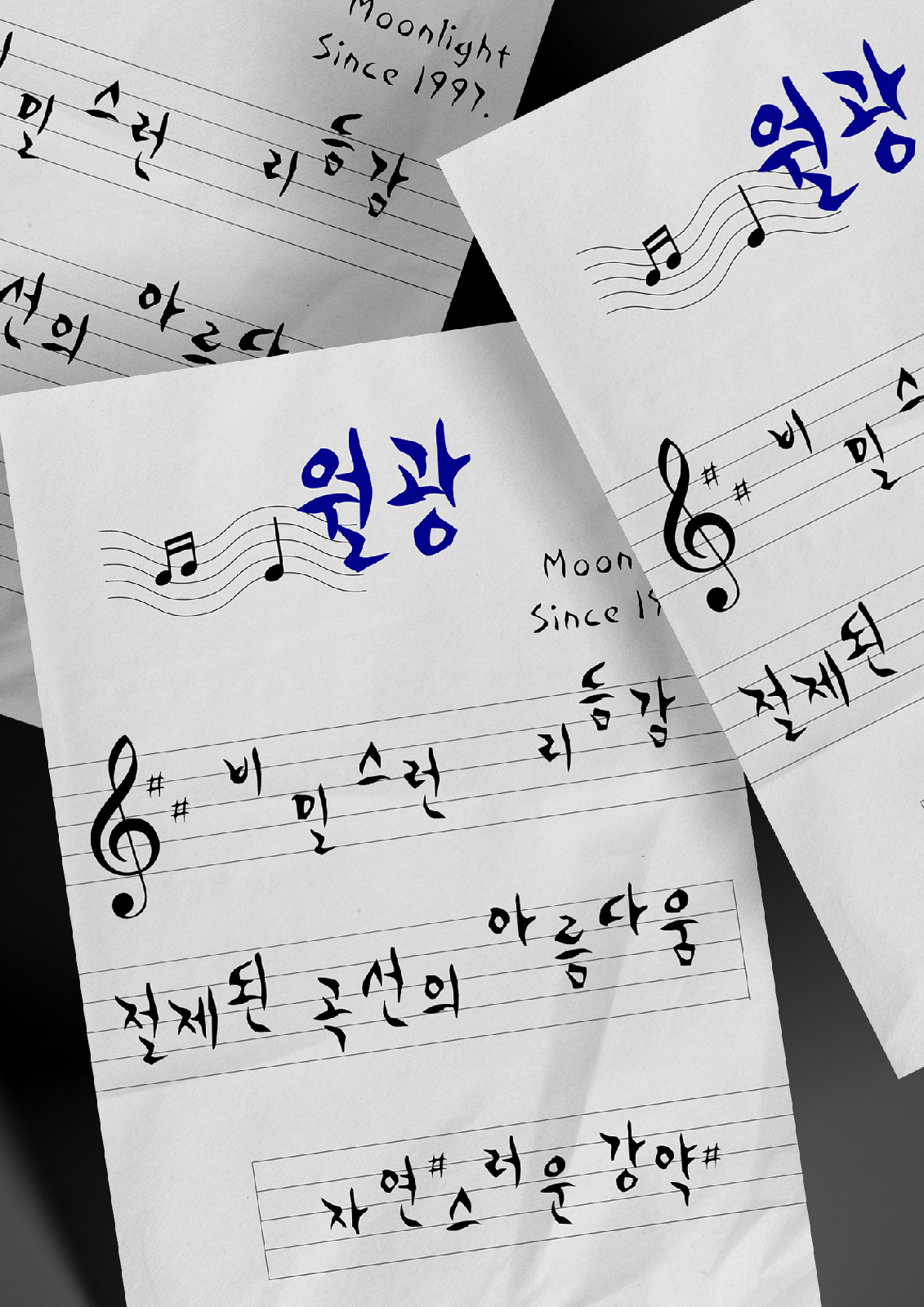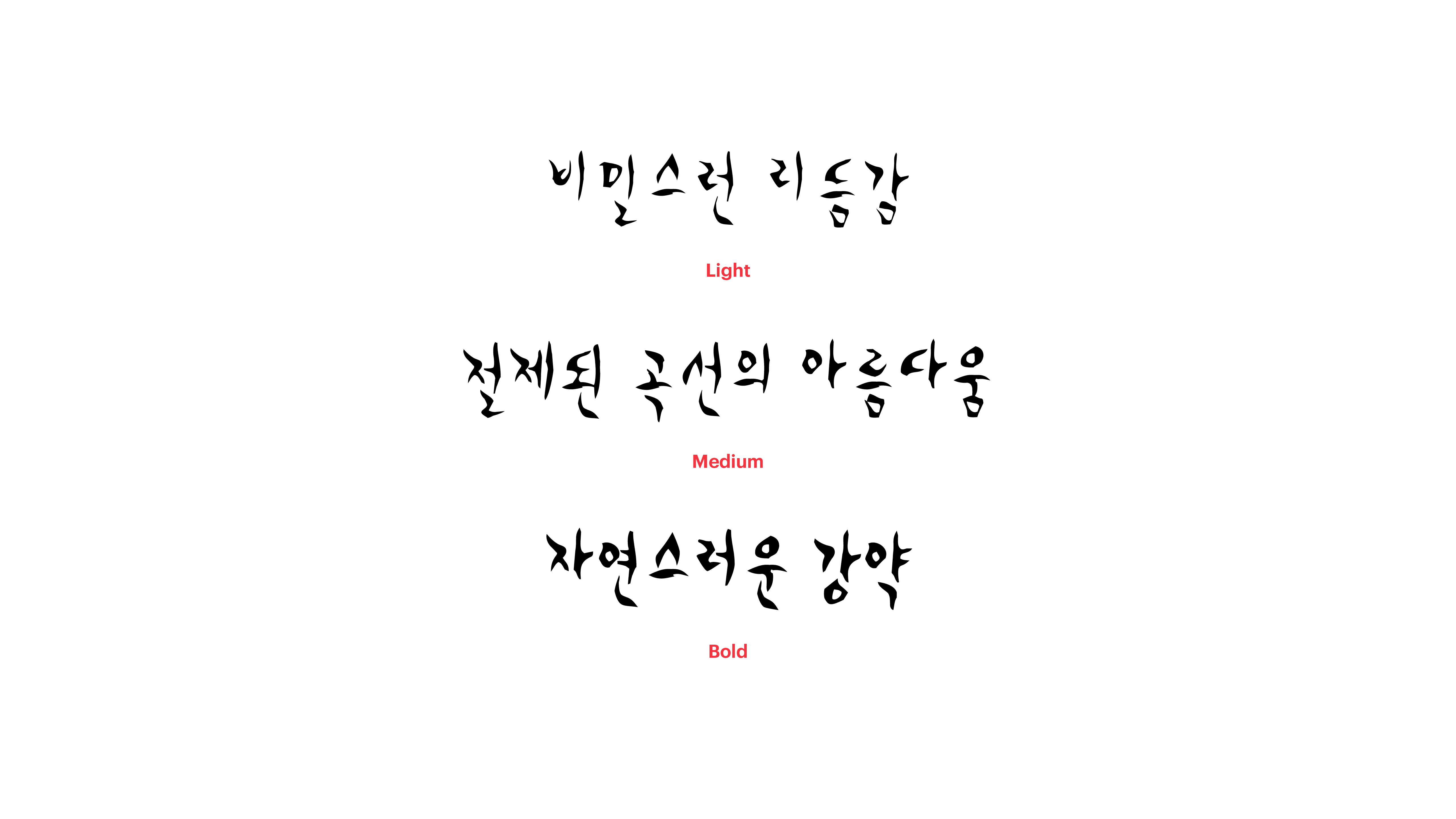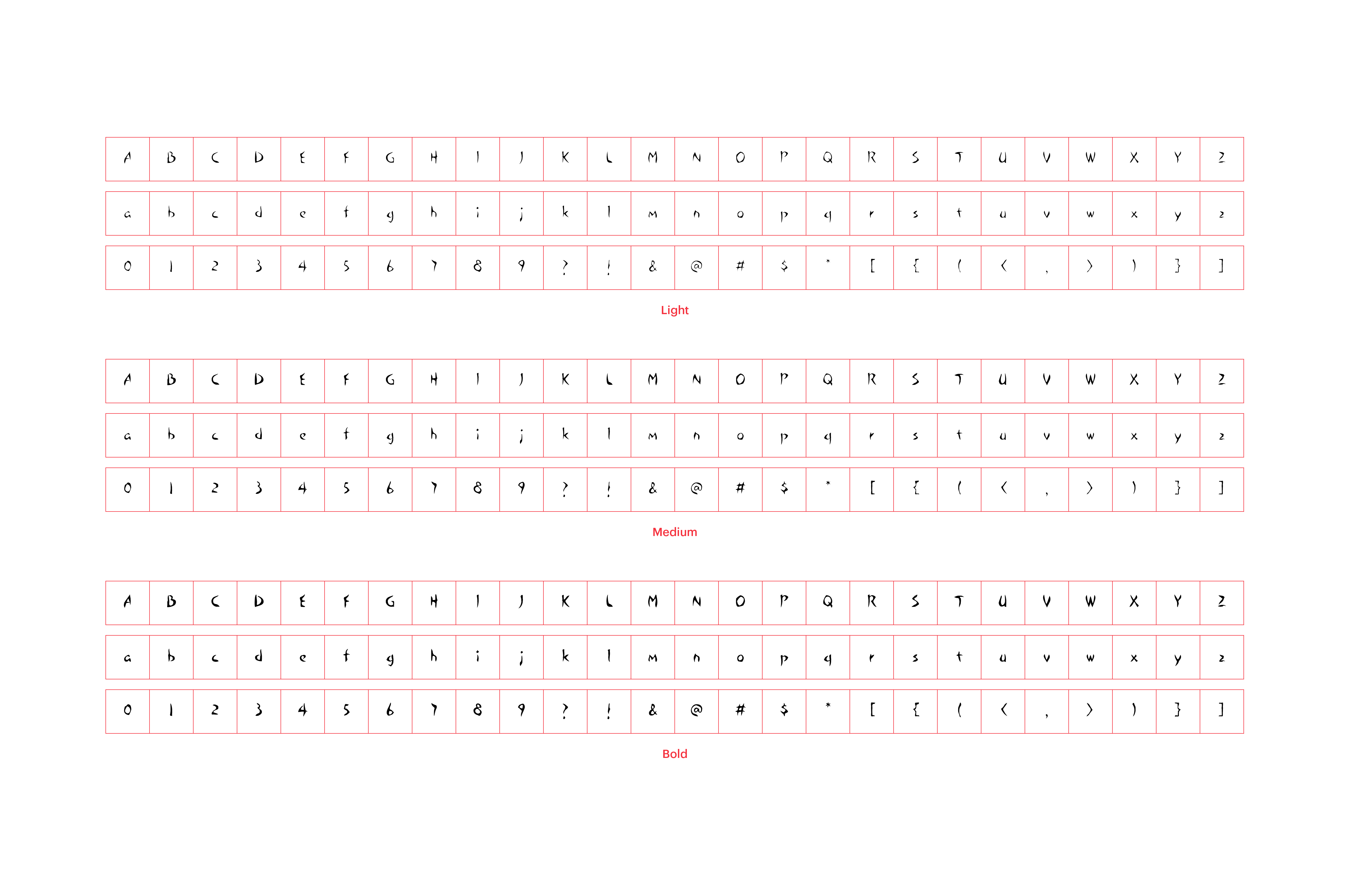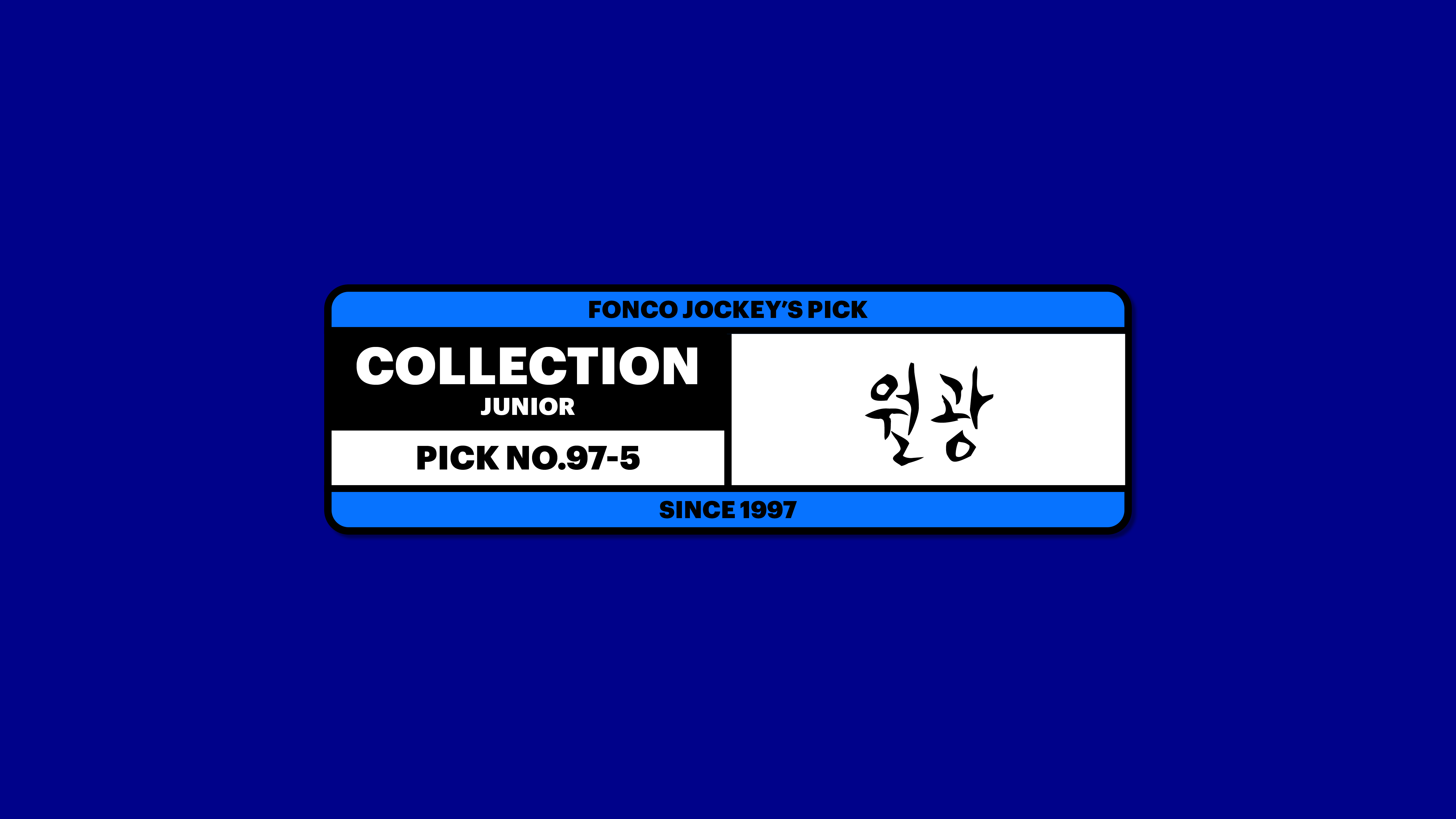
월광
Yoon 월광
달빛 아래에서는 폰트도 신비하게만 보일 겁니다. 월광체는 부드러운 달빛 그리고 삭망의 흐름에 담긴 비밀스런 리듬감을 절제된 곡선의 아름다움으로 표현하지요. 매일매일 조금씩 차오르거나 빠져나가는 달의 섭리와 같이, 자연스러운 강약을 지닌 폰트. 월광체와 함께 한밤의 신비한 기분을 표현해보세요.